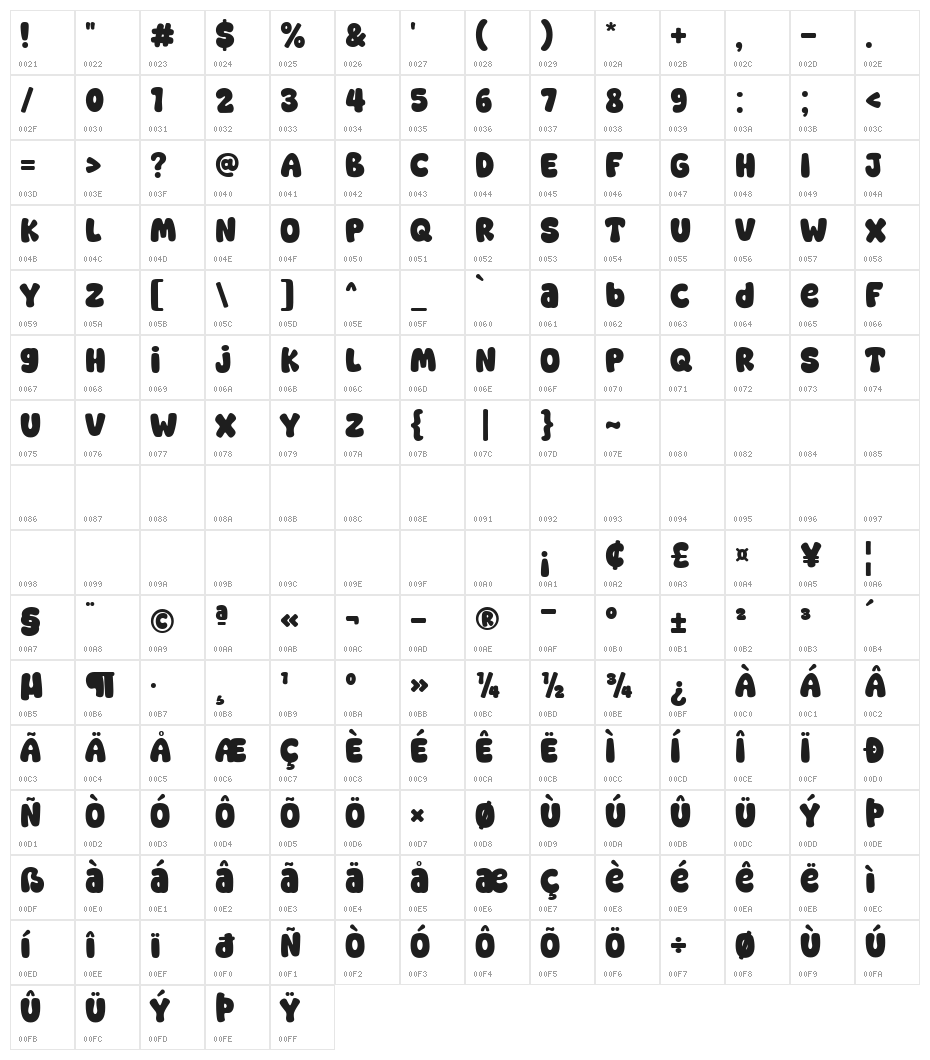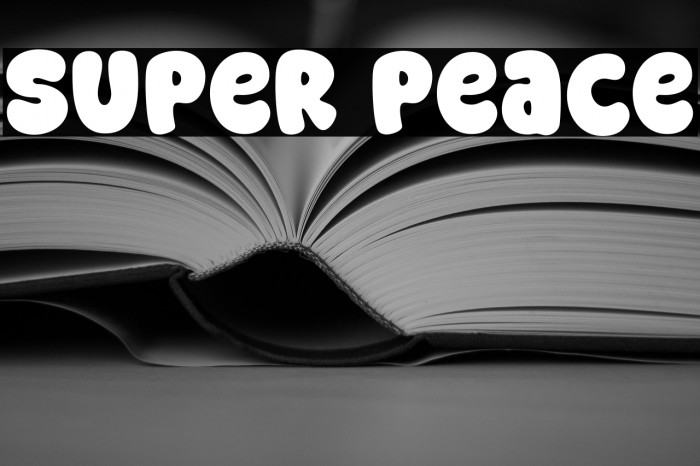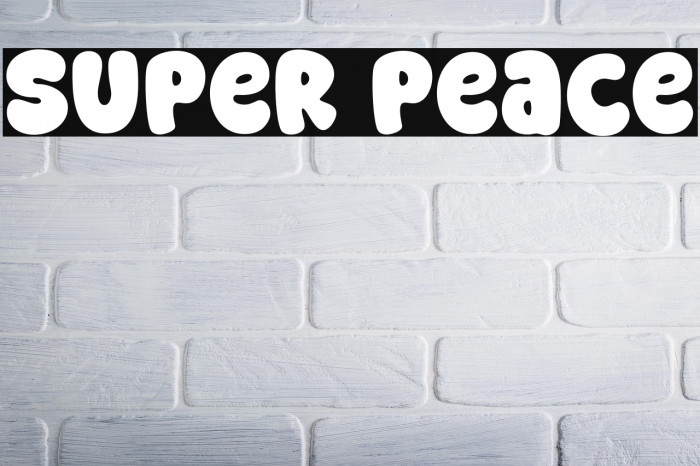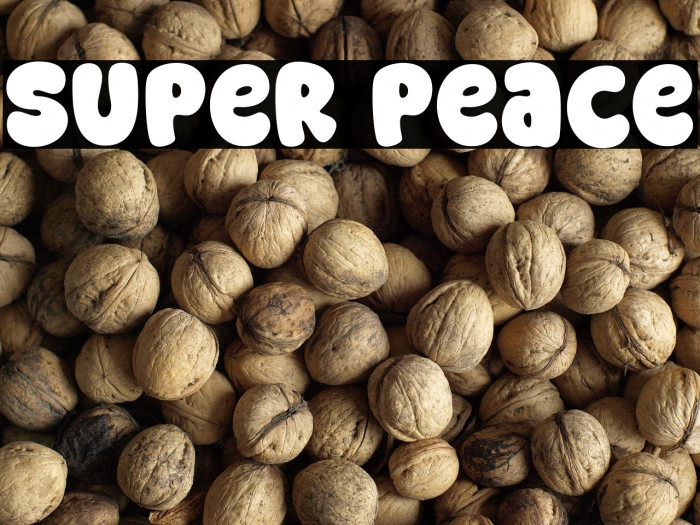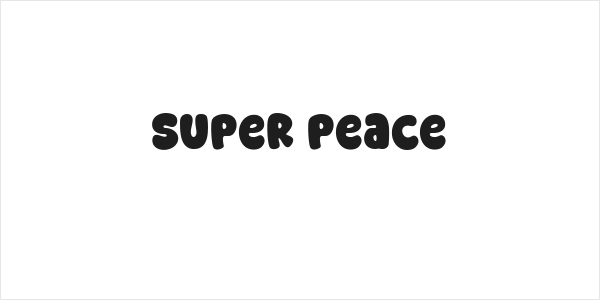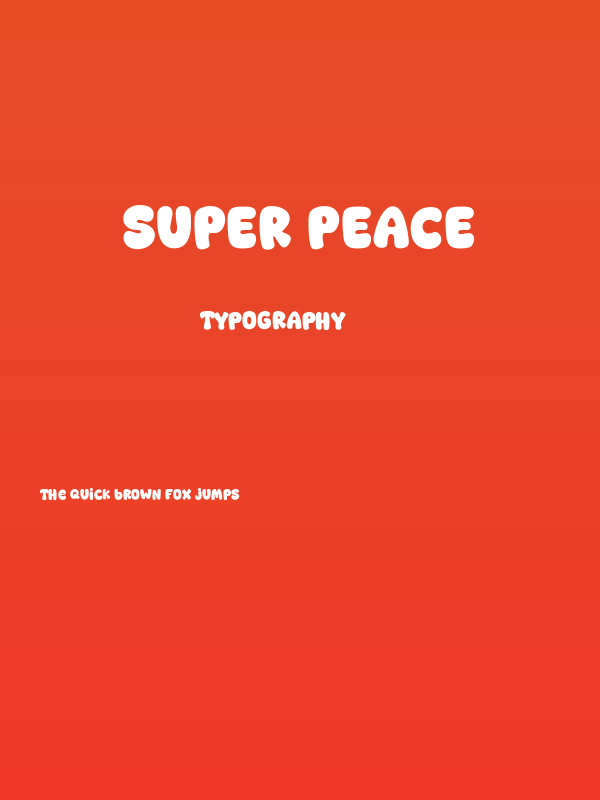
Super Peace Font
| 全体的なスタイル | Playful, Retro, Modern |
| 用途 | Headlines, Posters, Branding |
| おすすめプロジェクト | Ideal for children's books, playful branding, event posters, and any project requiring a fun and informal tone. |